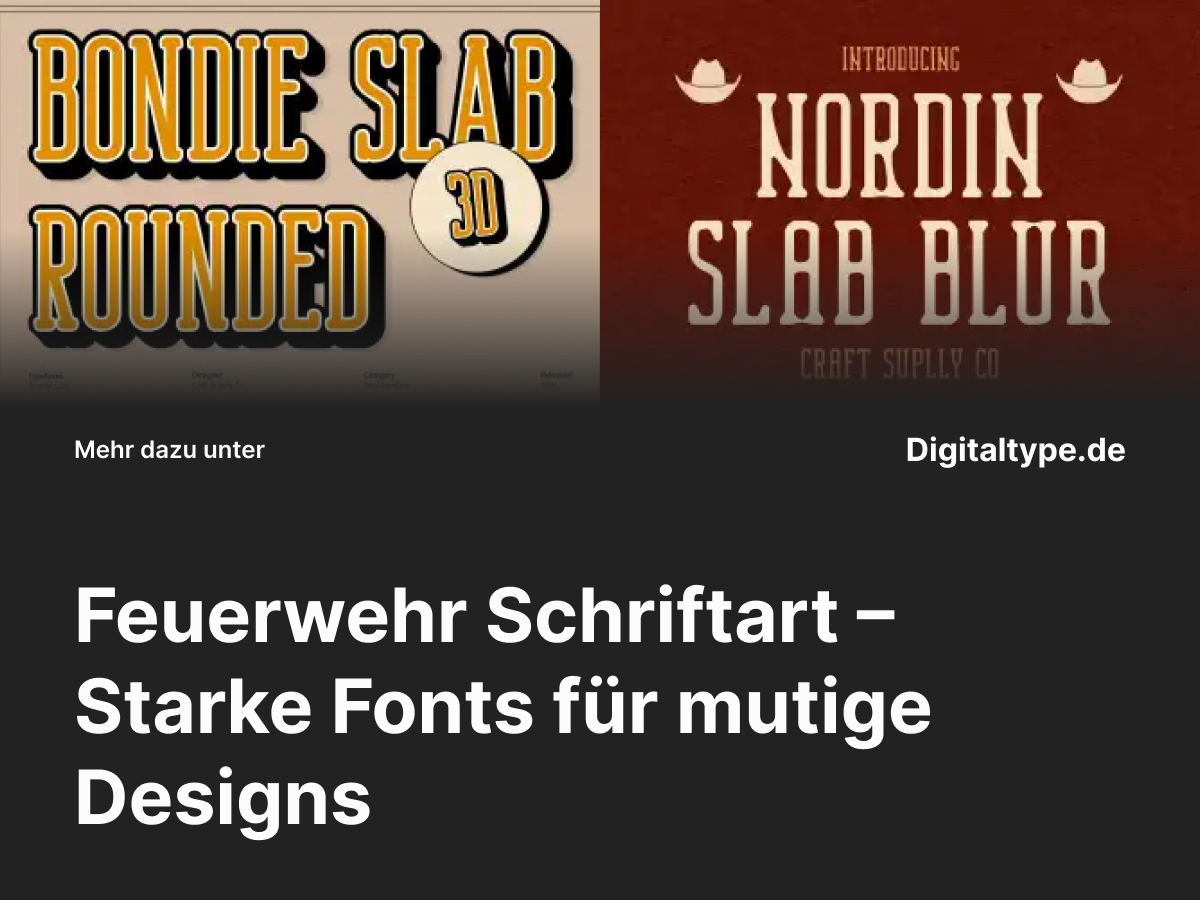
Feuerwehr Schriftart – Starke Fonts für mutige Designs
Wenn du an eine Feuerwehr Schriftart denkst, kommen dir sofort kräftige Buchstaben, klare Linien und ein Gefühl von Stärke in den Sinn.
Diese Fonts verkörpern Mut, Einsatzbereitschaft und Teamgeist – perfekt für Designs, die auffallen und Autorität ausstrahlen sollen.
Ob für Logos, Fahrzeuge, Poster oder Social-Media-Grafiken – Feuerwehr-Schriften verleihen deinem Design Kraft und Struktur.
Was ist eine Feuerwehr Schriftart?
Eine Feuerwehr Schriftart ist meist eine serifenbetonte oder blockartige Schrift, die Stabilität und Stärke vermittelt.
Diese Schriften sind oft inspiriert von typischen Einsatzfahrzeug-Beschriftungen oder Uniform-Aufdrucken und eignen sich ideal für Projekte, die Vertrauen und Energie ausdrücken.
Durch ihre markante, gut lesbare Struktur sind Feuerwehr-Fonts nicht nur für offizielle Designs geeignet, sondern auch für kreative Branding-Projekte, Plakate oder Sportdesigns.
Wann du eine Feuerwehr Schriftart verwenden solltest
• 1. Für Feuerwehr-Designs: Ideal für Vereinslogos, Fahrzeuge, Plakate und Ausrüstungsbeschriftungen.
• 2. Für Sport & Action-Projekte: Perfekt, um Dynamik, Kraft und Entschlossenheit zu betonen.
• 3. Für Branding & Logos: Eine robuste Schrift vermittelt Stärke und Professionalität.
• 4. Für Plakate & Kampagnen: Feuerwehr-Schriften ziehen durch ihre Klarheit sofort Aufmerksamkeit auf sich.
Die 6 besten Feuerwehr Schriftarten Alternativen
Hier sind sechs herausragende Feuerwehr Schriftarten, die Stärke, Klarheit und Designkraft vereinen – perfekt für Branding, Plakate und kreative Anwendungen.
1. Bondie Slab Rounded 3D
Bondie Slab Rounded 3D kombiniert kantige Stabilität mit runden Kanten – ideal für starke, dennoch freundliche Designs.
Perfekt für Logos, Poster und auffällige Branding-Projekte.
2. Nordin Slab Blur Font
Nordin Slab Blur bringt einen modernen Touch mit leicht verschwommenen Konturen.
Ideal für dynamische Feuerwehr-Designs oder Retro-inspirierte Plakate.
3. Hicked Slab Serif Font
Hicked ist kraftvoll, präzise und markant. Seine klaren Linien machen ihn perfekt für Einsatzfahrzeuge, Beschriftungen und sportliche Markenidentitäten.
4. Drefar Slab Serif Font
Drefar verbindet klassische Slab-Serif-Elemente mit moderner Lesbarkeit.
Ein vielseitiger Font für Poster, Uniform-Logos oder Werbematerialien.
5. Nordin Slab Condensed Serif
Diese kompakte Variante von Nordin sorgt für maximale Wirkung auf engem Raum – perfekt für Fahrzeugbeschriftungen oder plakative Designs mit klarer Struktur.
6. Bondie Condensed Slab Serif Font
Bondie Condensed kombiniert industrielle Stärke mit moderner Typografie.
Ein idealer Font für Branding, das Vertrauen und Power vermitteln soll.
Design-Tipps für Feuerwehr-Schriftarten
• 1. Verwende kräftige Farben: Rot, Schwarz oder Weiß unterstreichen den Feuerwehr-Look optimal.
• 2. Setze Schatten und 3D-Effekte ein: Damit wirken deine Schriften noch dynamischer.
• 3. Achte auf gute Lesbarkeit: Besonders bei Einsatzschriften zählt Klarheit vor Dekoration.
• 4. Kombiniere mit modernen Sans-Serif-Fonts: So entsteht ein harmonischer, professioneller Look.
Fazit: Feuerwehr Schriftart für starke Designs
Eine Feuerwehr Schriftart steht für Mut, Klarheit und Stärke. Sie eignet sich perfekt, wenn du Designs mit Charakter und Durchsetzungsvermögen gestalten möchtest.
Egal ob Branding, Plakat oder Fahrzeug – mit diesen Fonts setzt du ein starkes visuelles Statement.
Wähle deinen Favoriten, spiele mit Farbe und Layout, und erschaffe Designs, die genauso kraftvoll sind wie die Feuerwehr selbst.